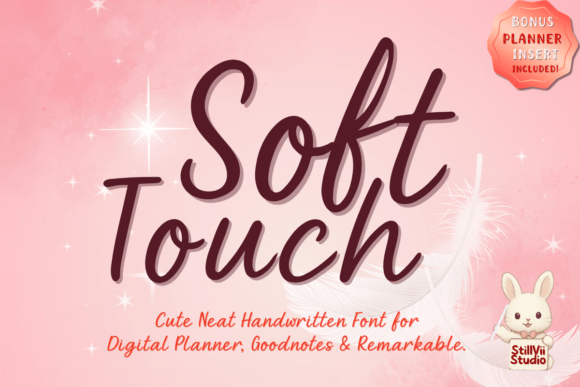
Soft Touch
Soft Touch – La police manuscrite qui révolutionne votre planner digital
Vous cherchez une police à la fois adorable et ultra‑lisible pour sublimer vos notes, vos journaux ou vos templates de planification ? Soft Touch est exactement ce qu’il vous faut. Conçue spécialement pour les étudiants, les journalers et les créatifs sur Etsy, cette police manuscrite combine chaleur authentique et organisation impeccable, que vous l’utilisiez dans GoodNotes, Notability ou tout autre outil de prise de notes.
Pourquoi choisir Soft Touch ?
- Design cute & cozy : chaque caractère ressemble à une écriture à la main, apportant une touche chaleureuse à vos projets.
- Lisibilité optimale : les lettres sont bien espacées et claires, idéales pour les listes, les titres et les paragraphes longs.
- Parfait pour Etsy : augmentez la valeur perçue de vos produits numériques (templates, planners, stickers) grâce à une typographie professionnelle et tendance.